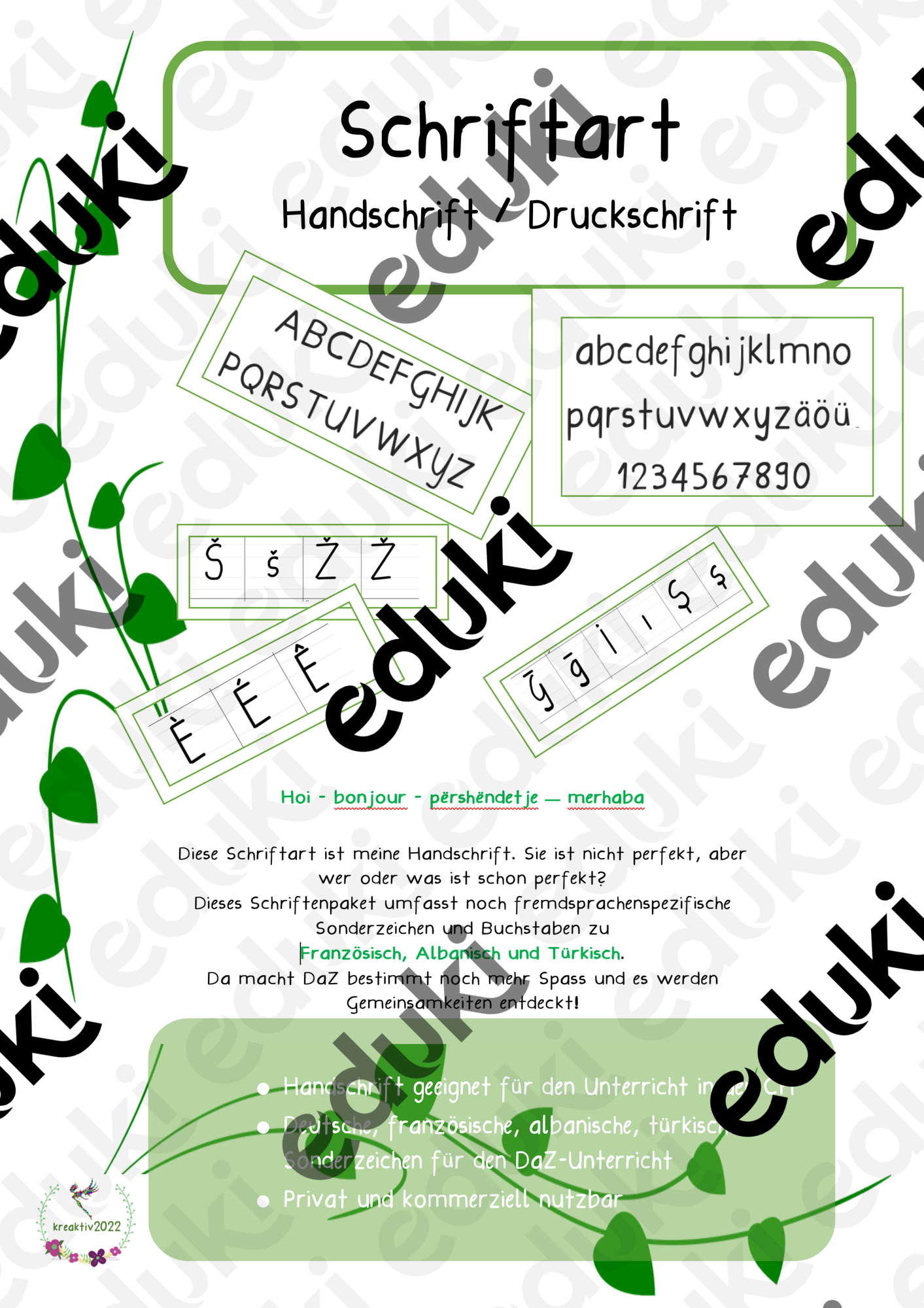
Diese Schriftart wurde mit meiner Handschrift erstellt und ist natürlich nicht perfekt. Ich benutze sie für meine Unterrichtsmaterialien im DaZ, in der BeGaFö und für den Regelunterricht in der Schweiz. Du kannst mit den entsprechenden Tastaturen die Sonderzeichen in den Sprachen Albanisch, Französisch und Türkisch benutzen.